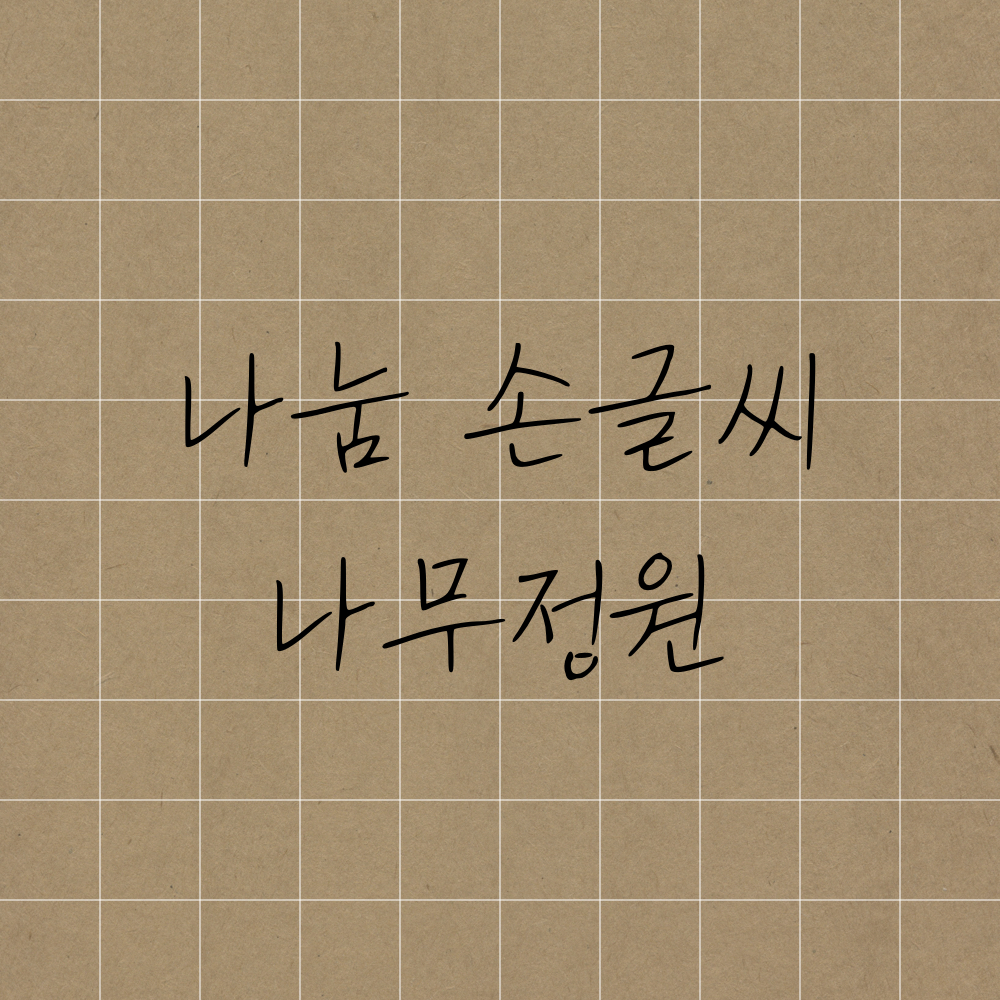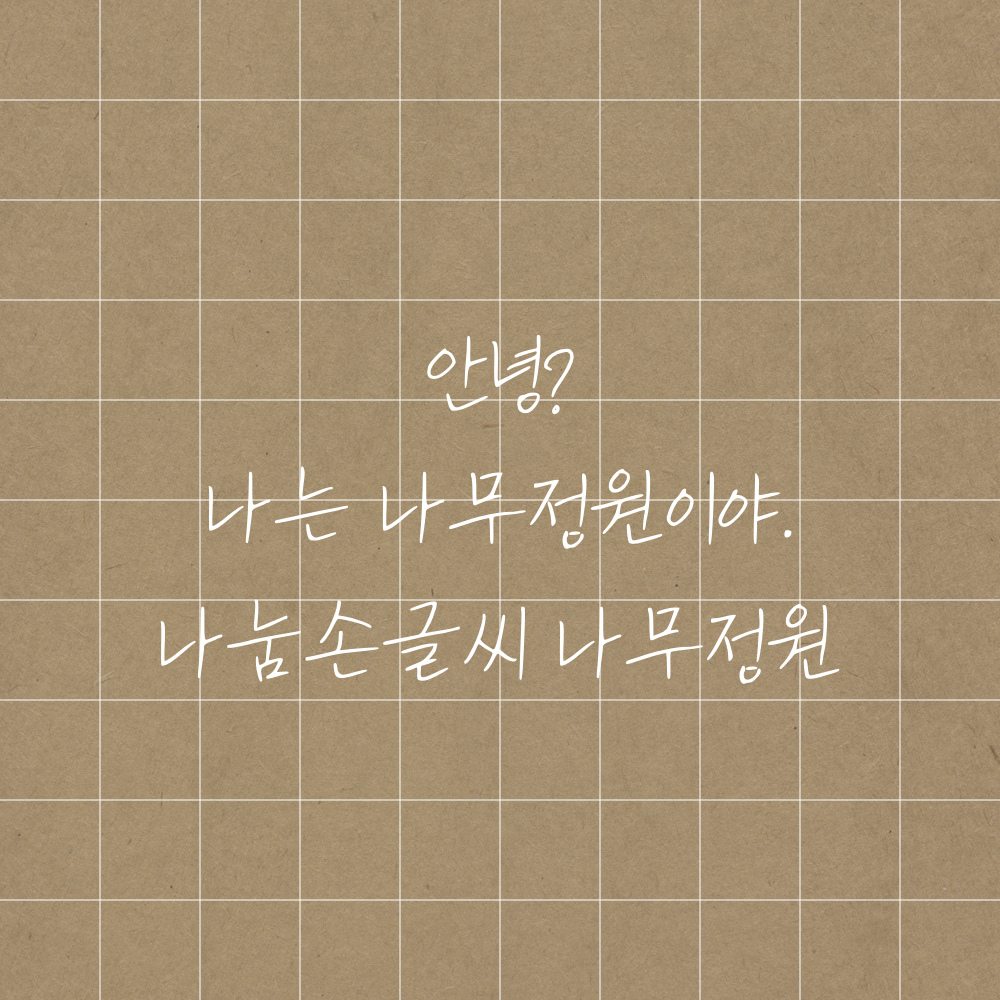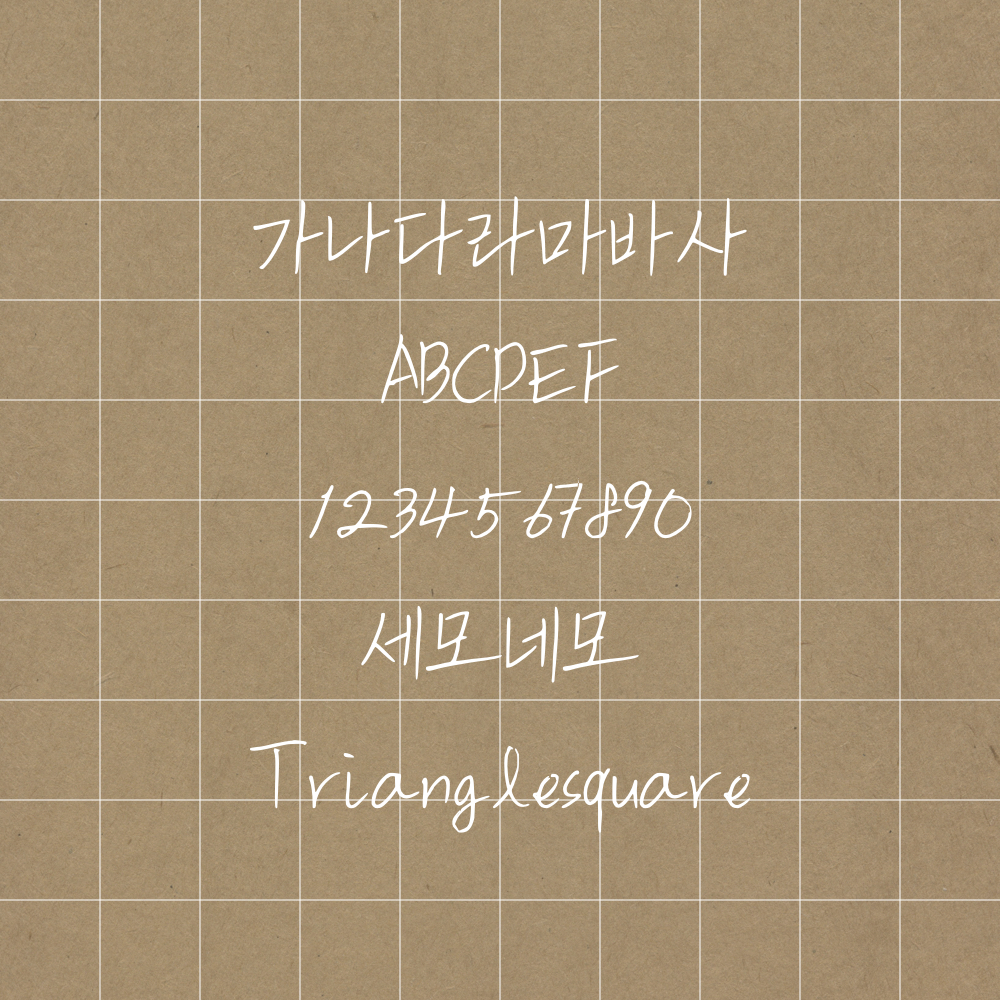
오늘의 폰트는 나무정원체입니다💕
얇은 글씨를 사랑하는 분들이라면 나무정원체가 제격입니다.작은 글씨 크기로 필기하는 것을 좋아한다면 오늘의 폰트에 집중해주세요~!!
미니 글씨에 적합한 폰트, 바로 살펴볼까요~?🤓
예시를 알아봅시다~!!🐿️
상세페이지에서 작게 작성하기 좋은 폰트네요. 색상, 종류, 추가 정보 등
얇은 글씨체 러버라면 나무정원체를 사용해보는건 어떠신가요~?❤️